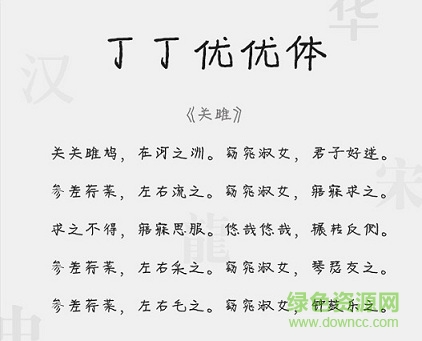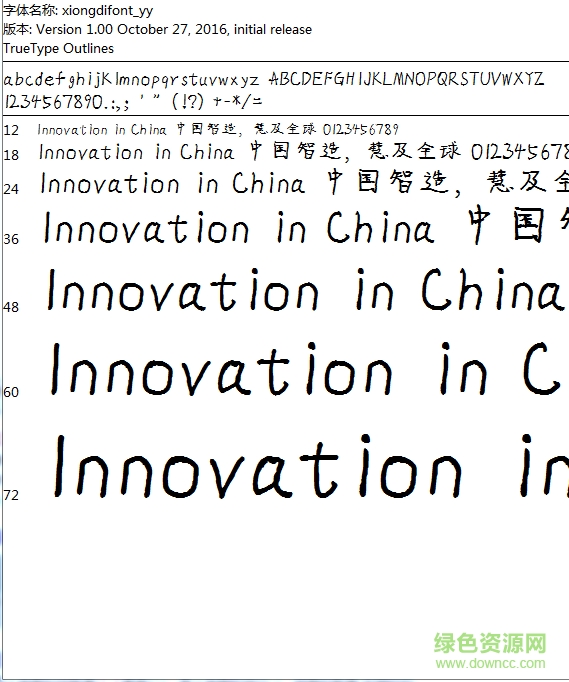
丁丁優(yōu)優(yōu)體是一款中文手寫字體軟件,字體得體大方,字里行間流露出放浪不羈的文雅氣息,十分好看,更多精彩字體下載盡在綠色資源網(wǎng)!
丁丁優(yōu)優(yōu)體字體是一款商業(yè)字體,該字體筆畫粗壯,尾部的甩尾有力且有豐富的筆觸細(xì)節(jié),大字效果突出且引人注目;并且最大程度還原作者書寫字形,細(xì)節(jié)表現(xiàn)完整,且字庫完整,可以廣泛應(yīng)用于名片設(shè)計(jì)、新聞媒體、宣傳海報(bào)、ppt、影視制作以及內(nèi)容用字等領(lǐng)域。
丁丁優(yōu)優(yōu)體這款字體屬于手寫字體,筆畫優(yōu)美整齊,筆觸情節(jié)好看,整體效果十分端莊優(yōu)雅,歡迎下載使用!